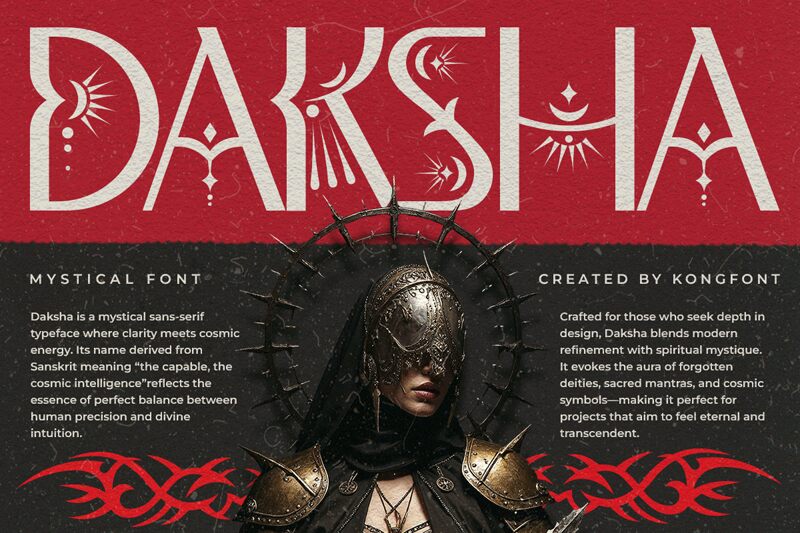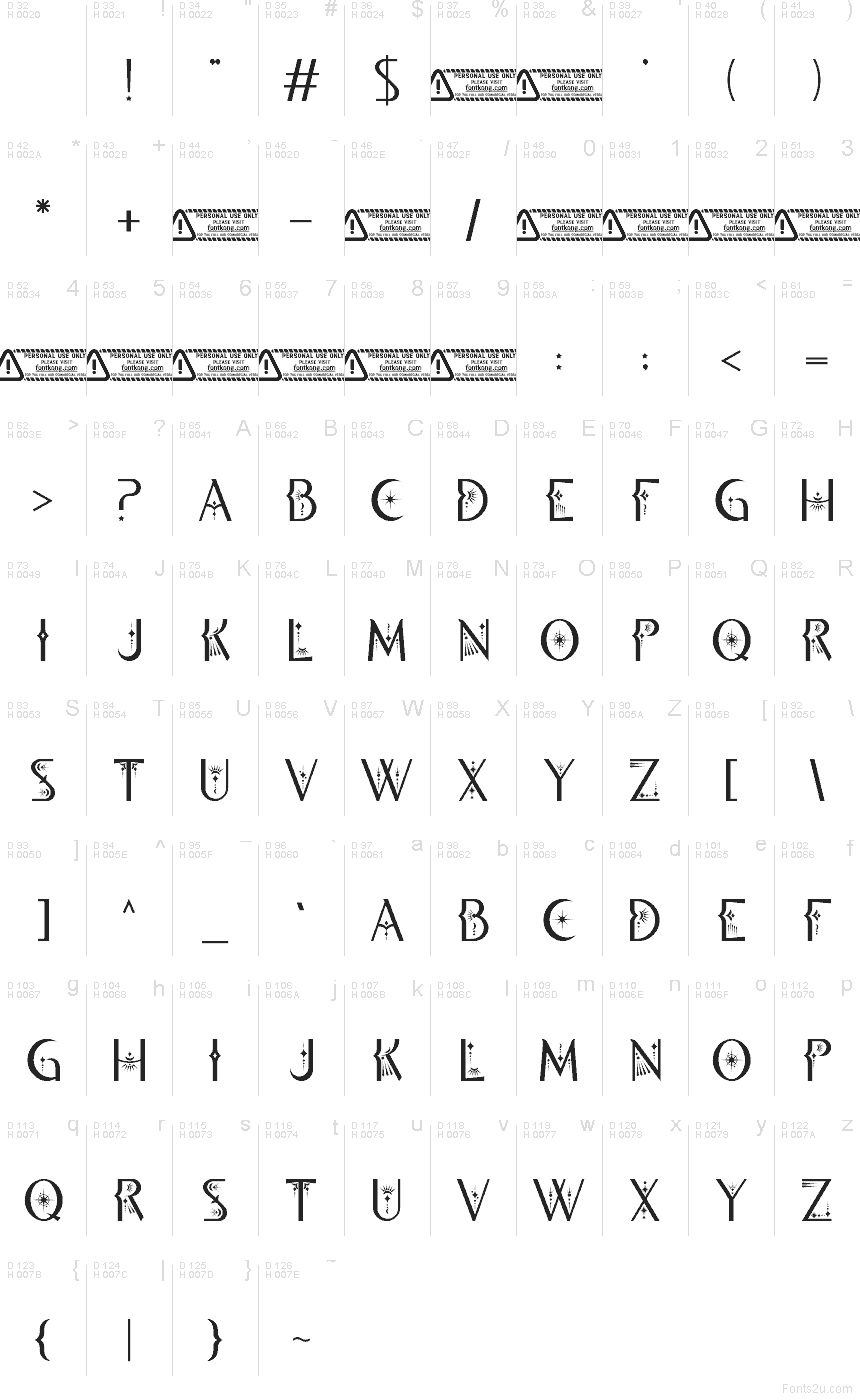
Daksha de Kong Font est une police d'affichage gratuite, ornementale et céleste, composée exclusivement de lettres capitales, qui dégage une esthétique décorative unique inspirée de l'Asie du Sud. Les lettres allient des formes élégantes et incisives à des motifs de lunes, d'éclats d'étoiles, d'accents pointillés et de rayons en éventail, conférant à cette police un aspect cérémoniel plutôt que purement décoratif.
Elle est parfaite pour les titres d'affiches, l'identité visuelle de festivals, les couvertures de livres, les en-têtes d'invitations et les cartons de titres, où quelques lettres suffisent à imprégner le texte de son atmosphère. En tant que police gratuite, Daksha est également idéale pour les monogrammes et les titres courts, car ses motifs cosmiques intégrés donnent aux mots, même les plus brefs, une présence emblématique affirmée.